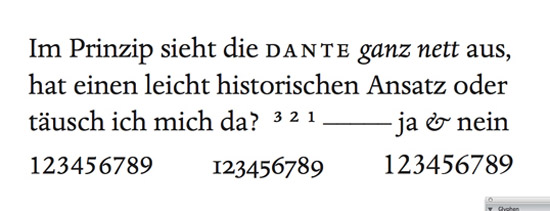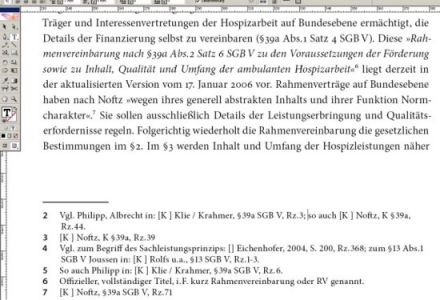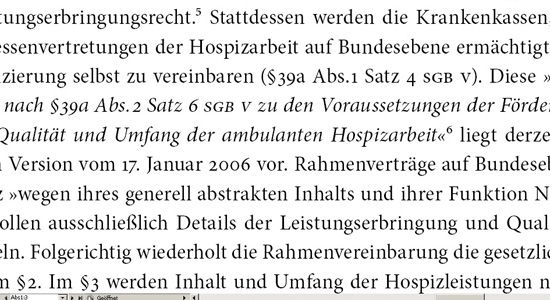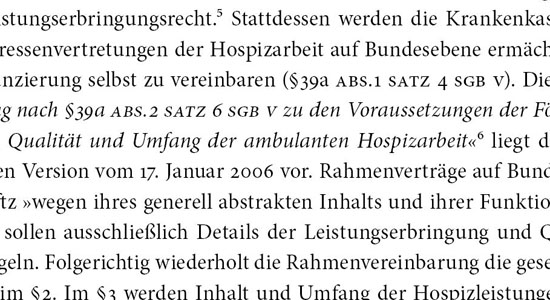
Mediäval- oder Versalziffern in juristischer Arbeit?
Mögen Juristen keine Mediävalziffern? Ich bin etwas unsicher ob ich in einer Diplomarbeit mit juristischer Thematik Mediävalziffern oder lieber die normalen Versalziffern einsetzen soll. Kennt jemand juristische Texte, die mit Mediävalziffern gesetzt sind?
Beispiel:
Sollte man grundsätzlich nur ein Ziffernformat einsetzen oder kann man die Fußnoten in Versalziffern setzen? Ich finde die Mediävalziffern in dieser Größe (Minion, 10pt.) schlechter lesbar als Versalziffern und habe deshalb letztere eingesetzt.
Wenn ich mir deinen Screenshot ansehe, würde ich an deiner Stelle komplett auf Versalziffern setzen.
Als "Beweisführung" ein sehr unruhiges Beispiel aus deinem Text –
… § 39a Abs. 2 Satz 6 SGBV zu den …
Ich würde das Pferd andersherum aufzäumen und SGBV in (echten, leicht gesperrten) Kapitälchen setzen. Dann fügen sich Ziffern und Abkürzungen wunderbar in das Spiel der Kleinbuchstaben.
Was man dann nicht mehr hat ist die implizite Hervorhebung, die solche Passagen in juristischen Arbeiten stets durch die Kombination Versalien und Versalziffern erfahren – der Text wird ruhiger.
Habe es ausprobiert - Versalziffern scheinen die bessere Wahl zu sein. SGB V als Kapitälchen fügt sich zwar gut ein - nutzt aber nichts, weil »Abs.« und »Satz« immer noch groß geschrieben sind:
Diese beiden auch noch in Kapitälchen zu setzen wirkt albern:
Das »Abs.« mutiert dabei zu »ABS« und könnte mißverstanden werden. Im Ergebnis wären wohl nicht typomanisch vorbelastete Menschen eher irritiert als vom besseren Lesefluß begeistert...
... wobei ... so aus der Ferne betrachtet ... man könnte sich daran gewöhnen, alles in Kapitälchen zu lesen...
Das »Abs.« mutiert dabei zu »ABS« und könnte mißverstanden werden.
Eben. Es heißt ja richtig "Abs.", das heißt der erste Buchstabe muß hier groß geschrieben werden, und dann dafür Kapitälchen finde ich albern.
Ich denke, wenn du auf "literarische Effekte" wie Mediävalziffern und SC verzichtest, und typografisch genauer arbeitest - gleich anmutende Wortabstände, Abstände generell optimieren, z.B. bei Zahlenkombinationen, Kombinationen aus Ziffern und Buchstaben usw. – dann hast du genug zu tun :D
Die »« würde ich aus Stilgründen durch „“ ersetzen, okay das mag vielleicht Geschmackssache sein, aber für mich wäre das dann nicht mehr angemessen.
Es gibt auch Schriften mit "Versalziffern", die kleiner als die Versalhöhe sind, z.B. bei der Dante MT, nur so nebenbei, quasi ein Zwischenschritt. Wie nennen sich diese, gibt es dafür eine Standardbezeichnung?
So. Kapitälchen sind gestorben, ich nehm' Versalziffern.
Ob die Ziffern der Dante einen speziellen Namen haben, weiß ich nicht. Ich weiß nur, daß mein Indesign in den OpenType-Funktionen zwischen »proportionalen Versalziffern« und dem »Standardzahlenformat« unterscheidet. Letzteres läuft etwas weiter, die Höhe der Ziffern bleibt aber gleich. (Das sollten wir dann wohl im Technikforum weiter diskutieren, oder?)
>Ich weiß nur, daß mein Indesign in den OpenType-Funktionen zwischen »proportionalen Versalziffern« und dem »Standardzahlenformat« unterscheidet.
Für den Fliesstext würde ich bei Versalziffern die Opentype-Variante "Proportionale Versalziffern" nehmen. Mit dem Standard-Versalziffernformat "Versalziffern für Tabellen" hast du Tabellenziffern (also die es ermöglichen sauber untereinander zu stehen, trotz unterschiedlicher Ziffernbreite). Siehst du hier den riesigen Abstand zwischen der "schmalen 1" und den darauffolgenden Ziffern.
Als Info, ich habe hier Indesign CS. Vielleicht haben sich in den neueren Versionen die Bezeichnungen im OT-Menu geändert?
Es gibt auch Schriften mit "Versalziffern", die kleiner als die Versalhöhe sind, z.B. bei der Dante MT, nur so nebenbei, quasi ein Zwischenschritt. Wie nennen sich diese, gibt es dafür eine Standardbezeichnung?
Das hatte ich einfach in die Runde gefragt … wie ist die Bezeichnung für solcherlei Ziffern.
Beispiel damit man sich das vorstellen kann
Minion Versalziffern | Dante Versalziffern
Versalziffern für Tabellen wären noch eine die dritte Form. Die hatte ich gleich außen vor gelassen, wegen der von Dir angesprochenen festen Breite (Dickte oder wie heißt das korrekt?). Das von mir angesprochene Standardzahlenformat entspricht den normalen Zahlen auf die Word und Co. zugreifen, ohne OpenType-Attribute zu verwenden - die Breite liegt irgendwo zwischen den proportionalen- und den Tabellenziffern.
1. In juristischen Texten lieber Versalziffern.
2. Ich merke mir die Begriffe (spezielle) Kapitälchenziffern oder Dreiviertelziffern (wundert mich, daß die in der Typo-Bibel »Detailtypografie« nicht erwähnt werden?).
3. Wenn ich mal ein Buch schreibe, in welchem nicht alle drei Zeilen ein Paragraf vorkommt, werde ich an die Dante denken – ist ja inzwischen auch als OpenType-Variante erhältlich.